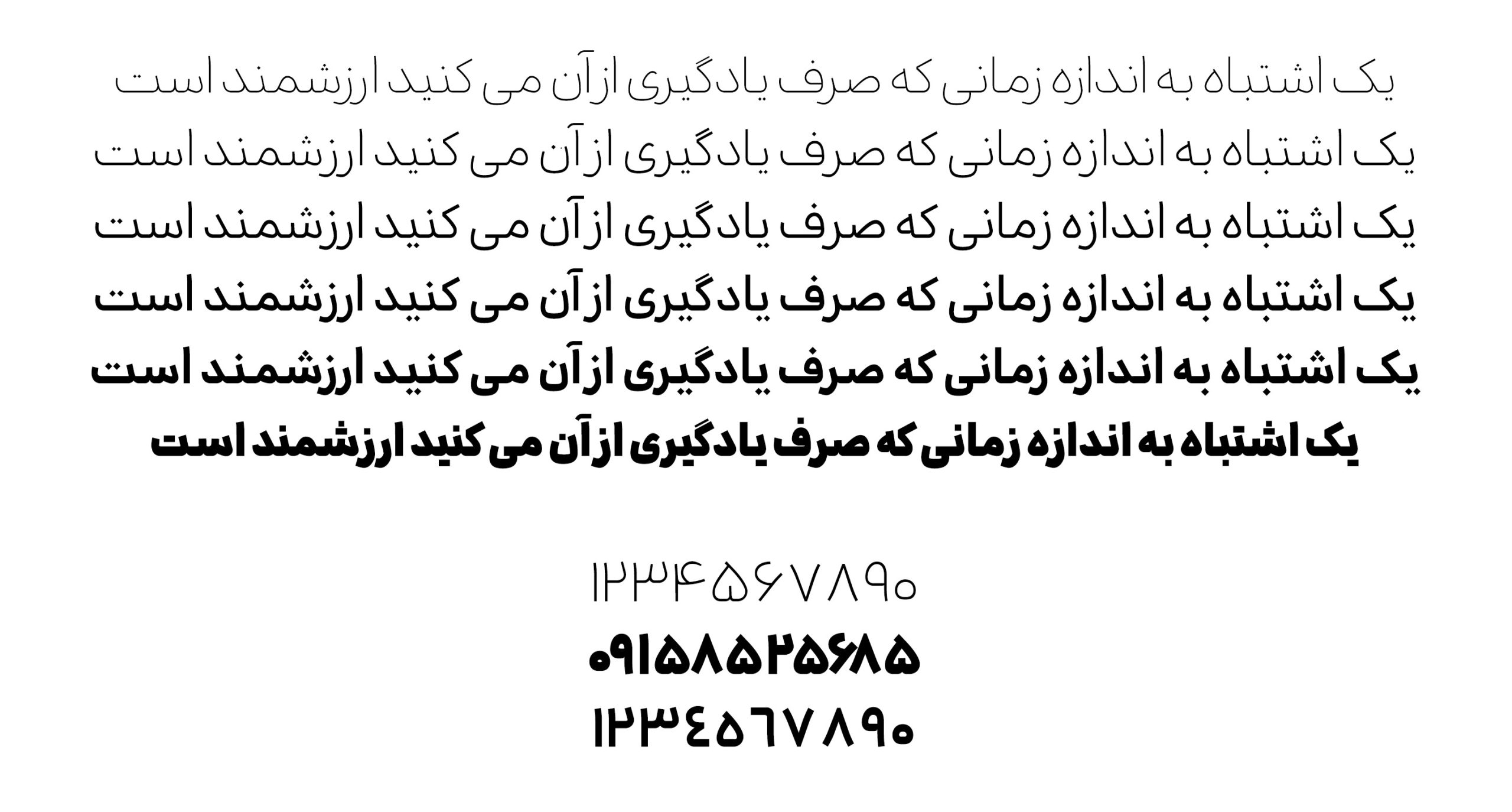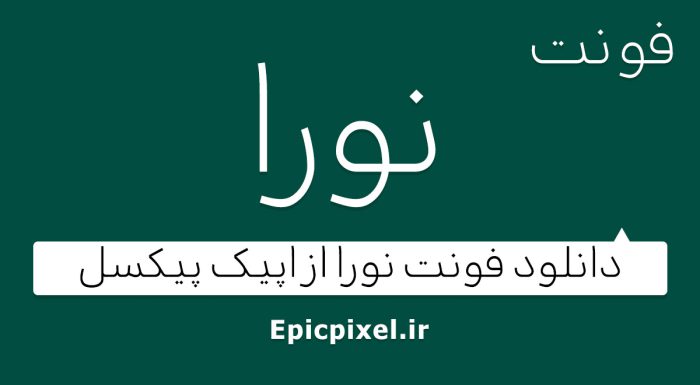
فونت نورا، یک انتخاب هوشمندانه برای طراحان و وبمسترانی است که به دنبال فونتی مدرن، خوانا و کارآمد برای پروژه های فارسی خود هستند. این فونت از ابتدا با هدف استفاده در دنیای دیجیتال طراحی شده و به همین دلیل، در نمایشگرها و رزولوشن های پایین نیز وضوح بسیار خوبی دارد. فرم نوشتاری حروف نورا به گونه ای است که در برابر پیکسل ها به خوبی عمل می کند و خوانایی متن را حتی در اندازه های کوچک تضمین می کند.
یکی از ویژگی های برجسته نورا، تنوع وزن های آن است که به شما اجازه می دهد تا در طراحی های مختلف، از وزن های نازک برای متن های ظریف تا وزن های ضخیم برای عناوین جذاب استفاده کنید. این تنوع، دست شما را در طراحی باز می گذارد و به شما کمک می کند تا به بهترین شکل ممکن، پیام خود را به مخاطب منتقل کنید.
علاوه بر این، فونت نورا با پایبندی به اصول خوشنویسی فارسی، هویتی اصیل و در عین حال مدرن دارد. طراحان این فونت تلاش کرده اند تا در کنار لحن مدرن، هویت نوشتار فارسی نیز حفظ شود. دندانه های بلند، حلقه های بزرگ و تعادل در فضای بین حروف، از جمله ویژگی هایی هستند که به خوانایی و زیبایی این فونت افزوده اند.
اگر به دنبال فونتی هستید که هم در فضای دیجیتال و هم در چاپ، عملکرد بی نظیری داشته باشد و در عین حال، هویت و اصالت نوشتار فارسی را نیز حفظ کند، فونت نورا بهترین گزینه برای شماست. این فونت با ویژگی های منحصر به فرد خود، به پروژه های شما جلوه ای خاص و حرفه ای می بخشد.